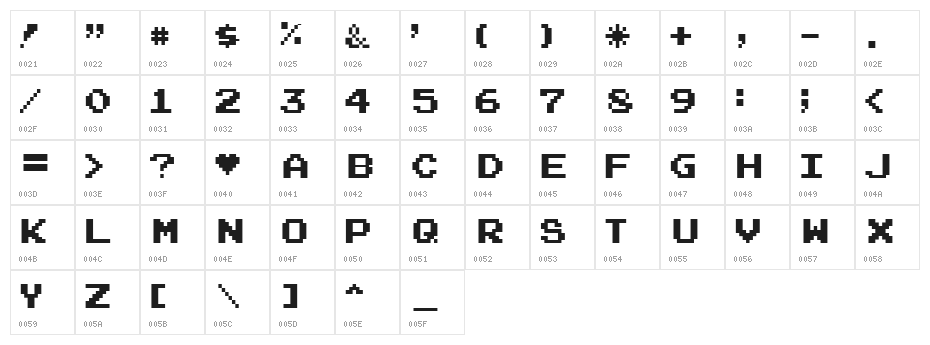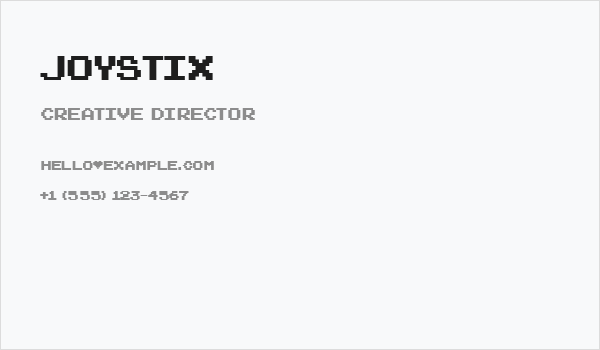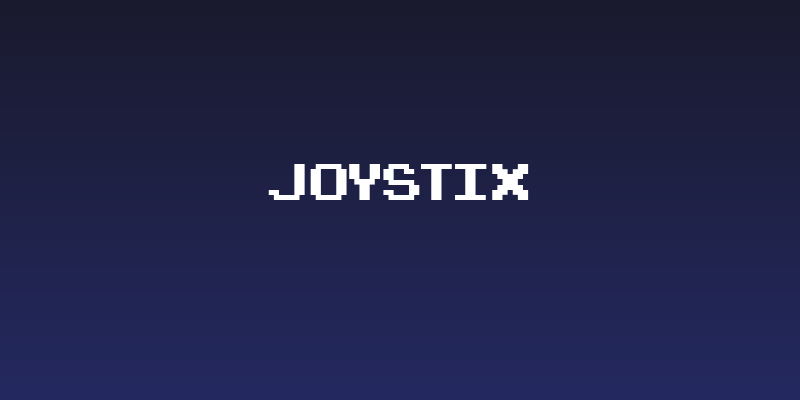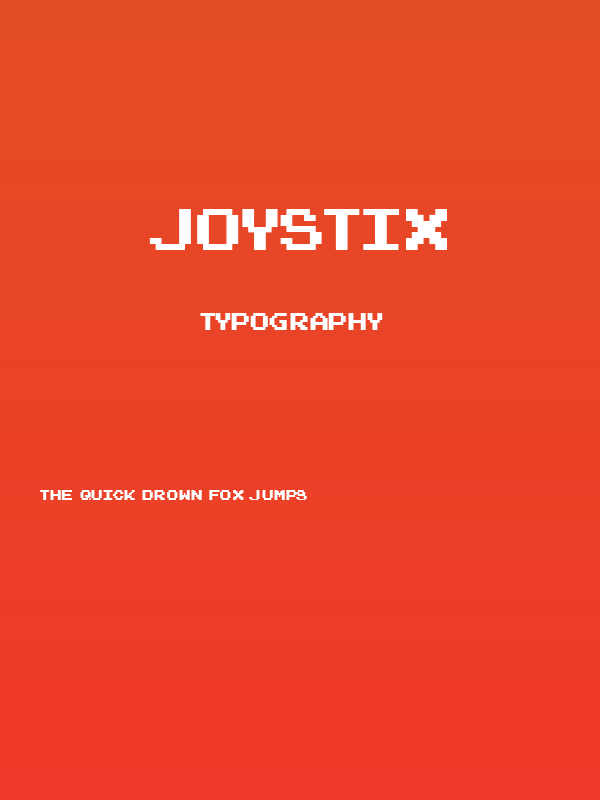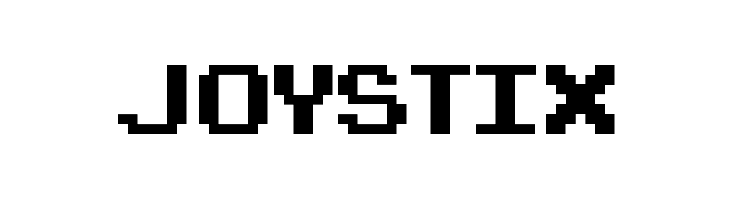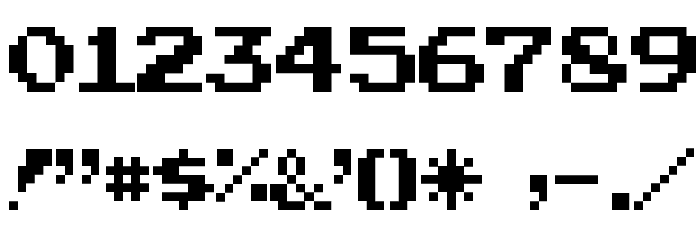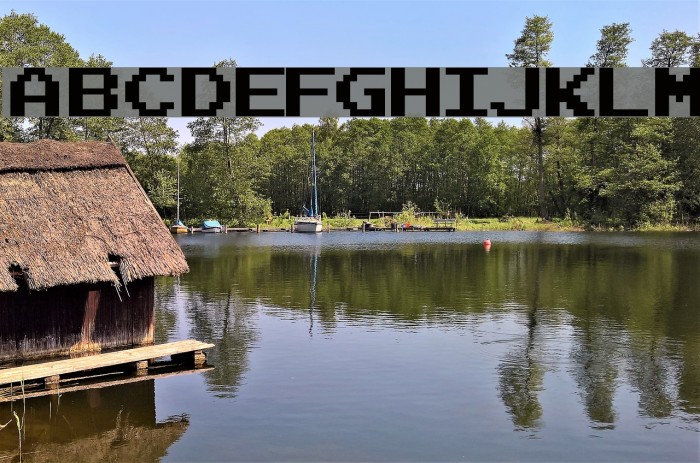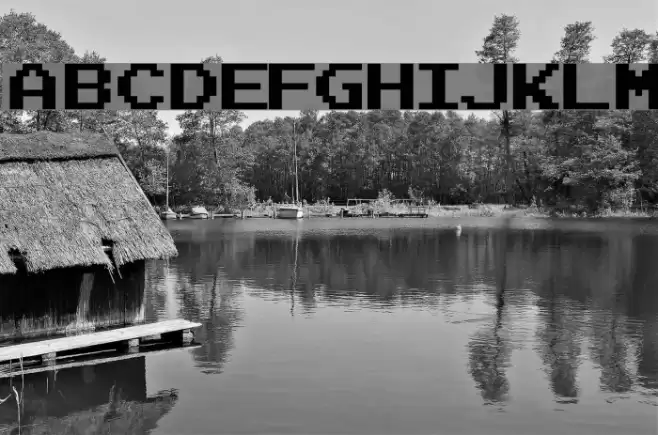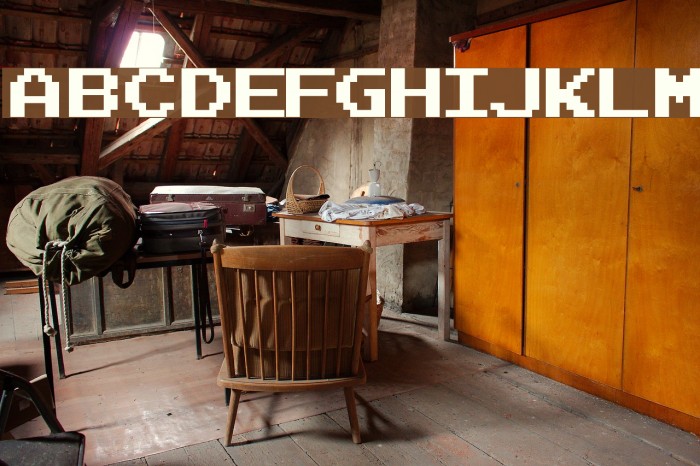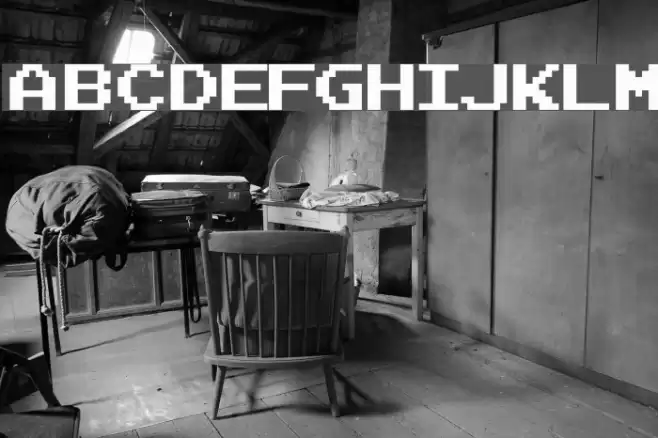
Joystix Font
| Gesamtstil | Retro |
| Anwendungsfall | Headlines, Logos, Digital Art |
| Vorgeschlagene Projekte | Ideal for video game designs, retro-themed posters, digital art projects, and any creative work that seeks to capture the essence of classic arcade aesthetics. |